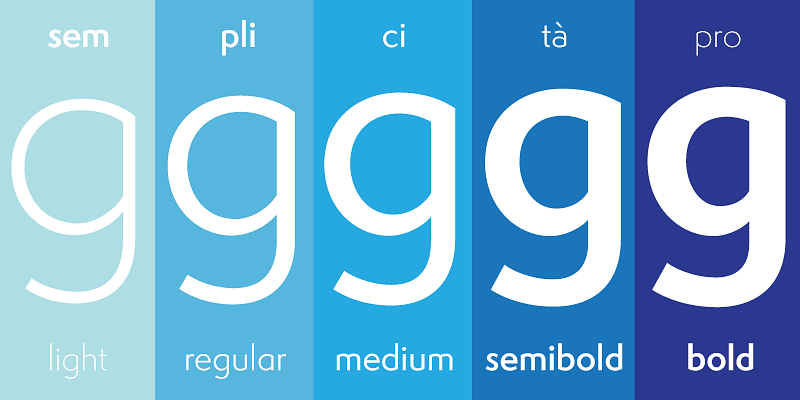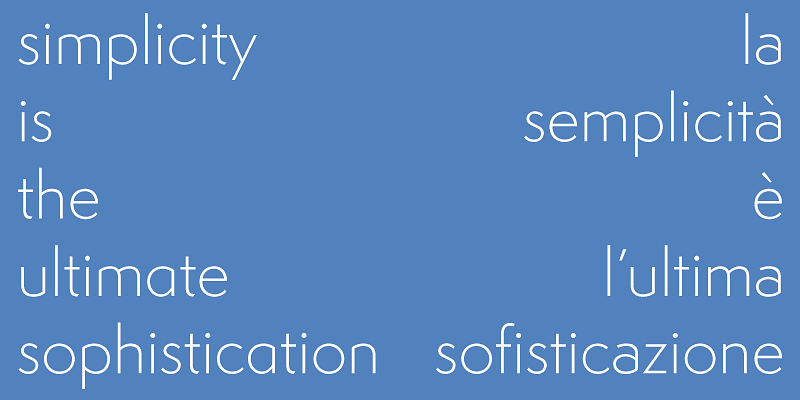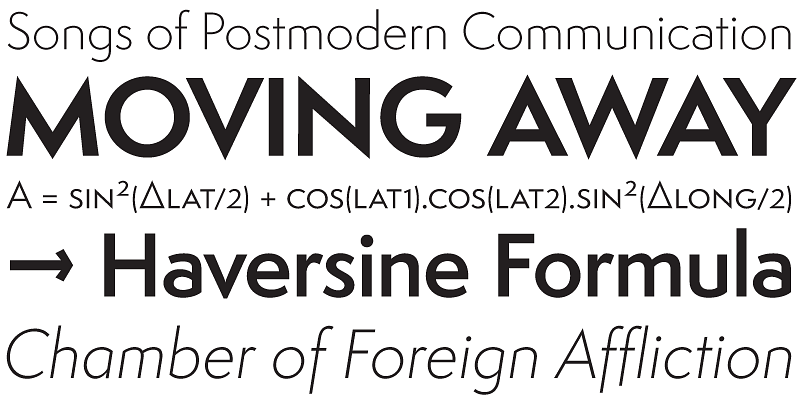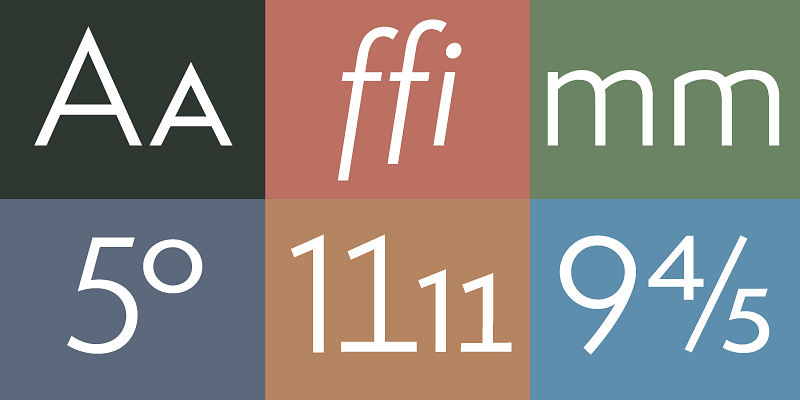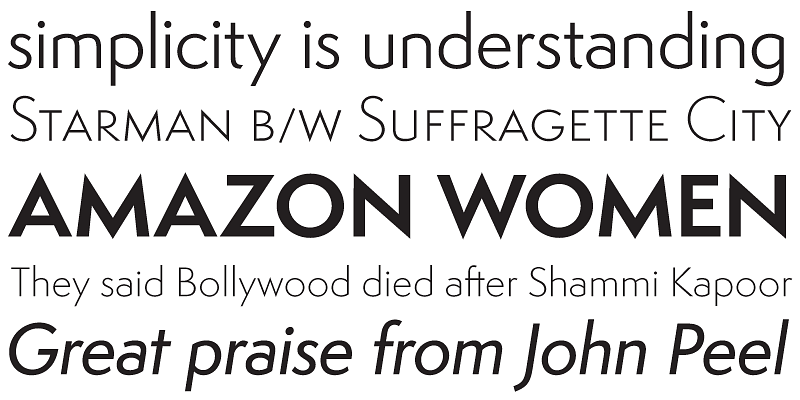
Semplicita Pro ist eine Weiterentwicklung aus dem 21. Jahrhundert des bahnbrechenden Nebiolo-Designs von 1930, das die kühle teutonische Geometrie der Futura durch die warmen, humanistischen, kalligrafischen Buchstabenformen der italienischen Renaissance ersetzt.